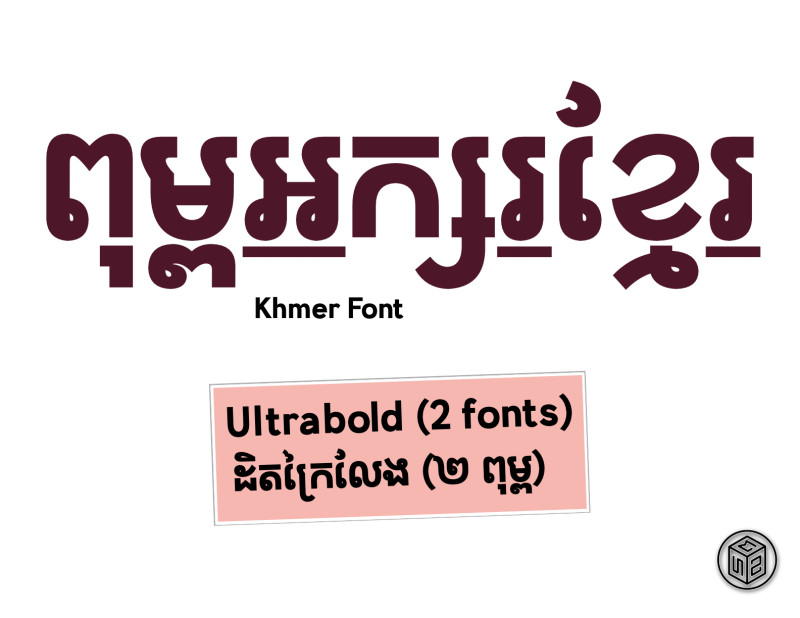
Single download file of the classic san serif style Khmer font - Leelhaa Ultrabold and Ultrabold Italic
ពុម្ពអក្សរដ៏ស្រស់ស្អាតដែលបានរចនាឡើងឲ្យមានអំណានល្អប្រសើរ និងភាពទស្សនាមុតមាំហៅថា Leelhaa Pro - មានកម្រស់ ៦ ប្រភេទ ខុសៗគ្នាពី ធម្មតា ដល់ ខ្មៅ! ប្រើពុម្ពអក្សរនេះសម្រាប់ការបង្កើត ក្រាហ្វិច ការផ្សាយពាណិជ្ជកម្ម និមិត្តសញ្ញា និង ស្លាកយីហោដ៏ស្រស់ស្អាត សមស្របជាអក្សរធំបង្ហាញ ឬក៏អក្សរក្នុងអត្ថបទ។
Leelhaa Pro, the beautiful Khmer typeface designed for high readability and visibility - features 6 different weight class from Regular to Black. Use this font to create beautiful graphics, advertisements, logos, and banners ideal for Display or Text.